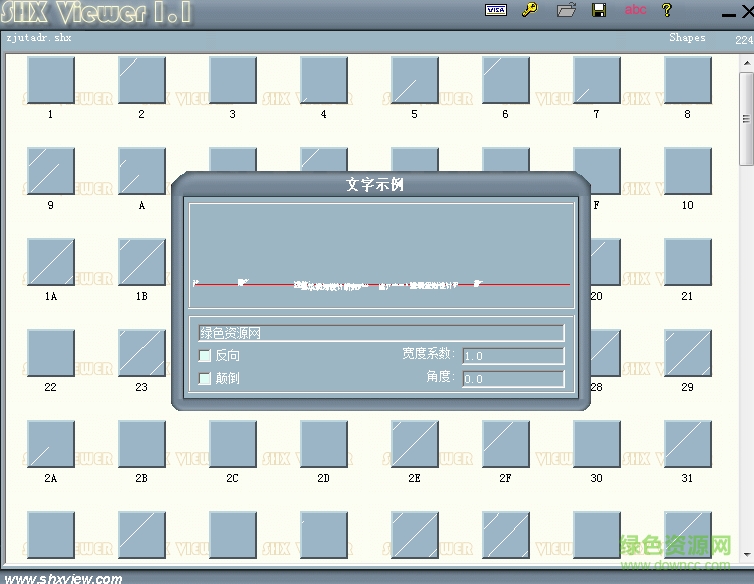
zjutadr ltd1.shx
zjutadr.shx是一款cad2004專用字體文件,該字體非常的漂亮,如果大家因?yàn)槿鄙賨jutadr.shx而無法打開文件,下載文件即可喲`
什么是cad字體?
1.文字的外在形式特征。就是文字的風(fēng)格,是文字的外衣。 字體的藝術(shù)性體現(xiàn)在其完美的外在形式與豐富的內(nèi)涵之中。 字體是文化的載體,是社會(huì)的縮影。
CAD字體主要是為CAD軟件提供顯示輔助,跟普通字體實(shí)際是一樣的意思